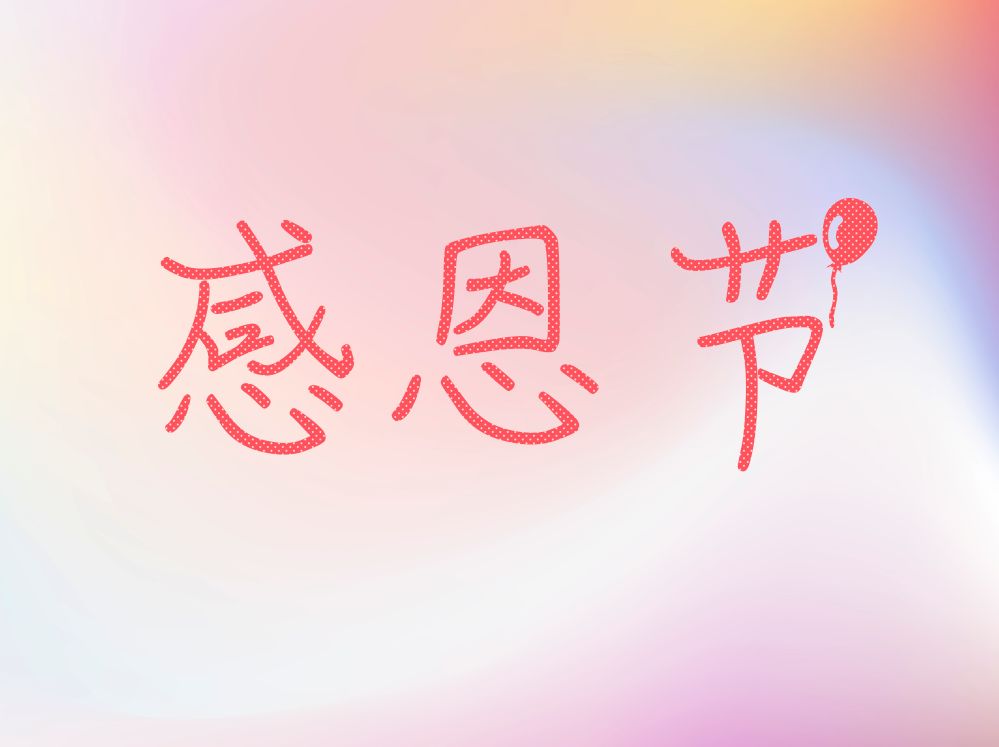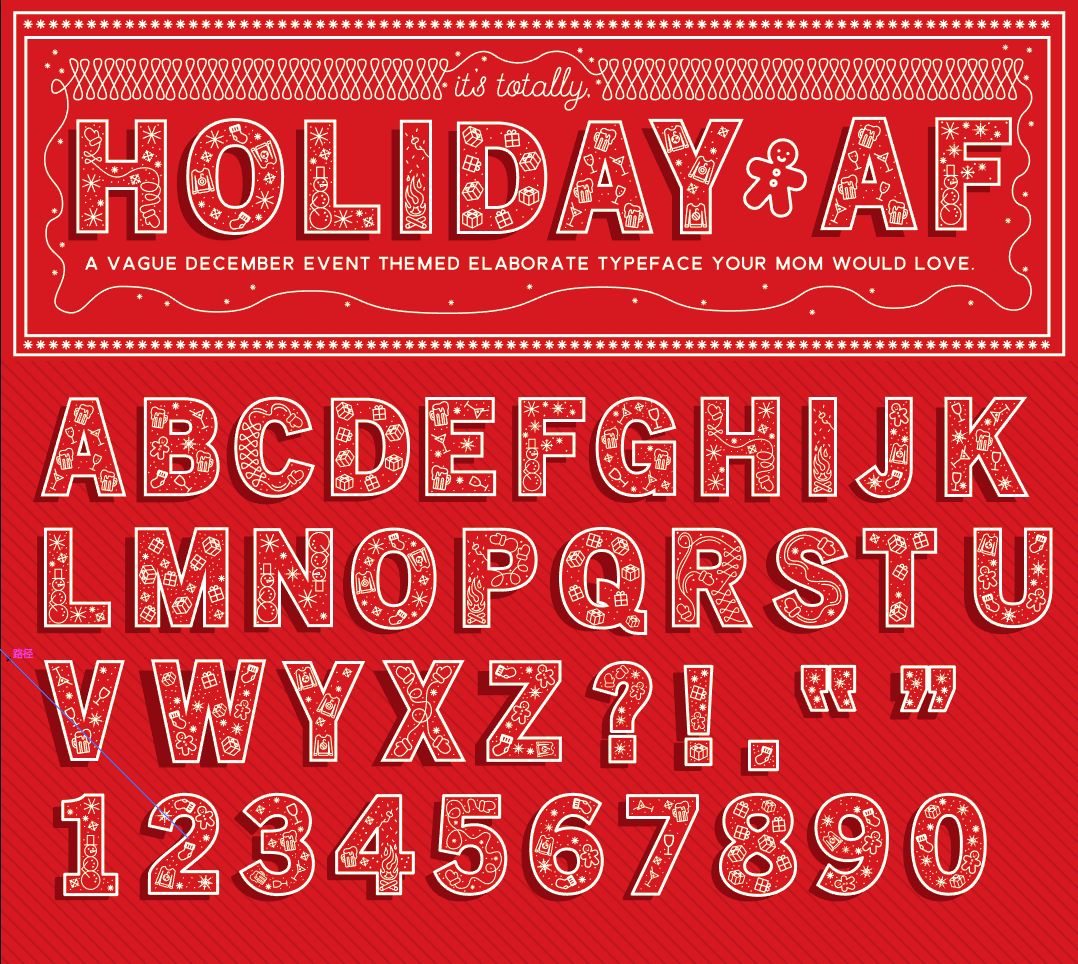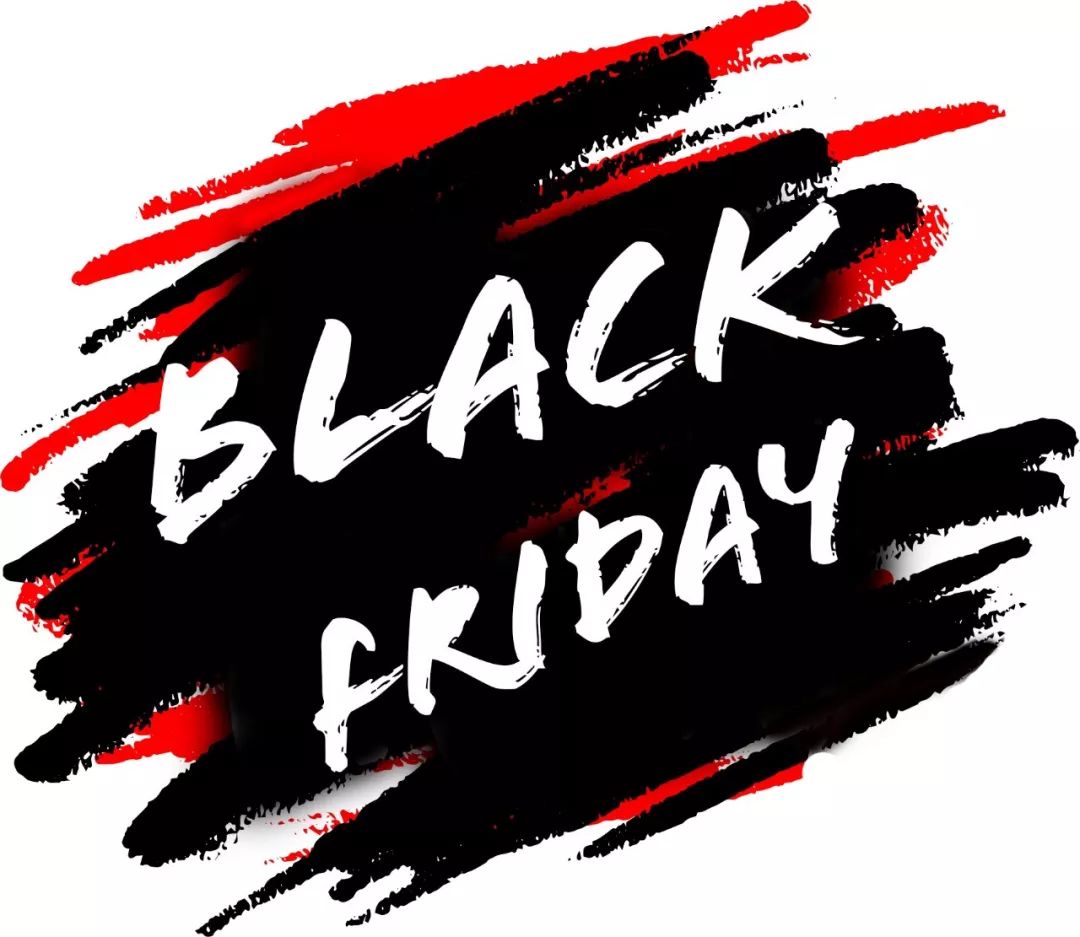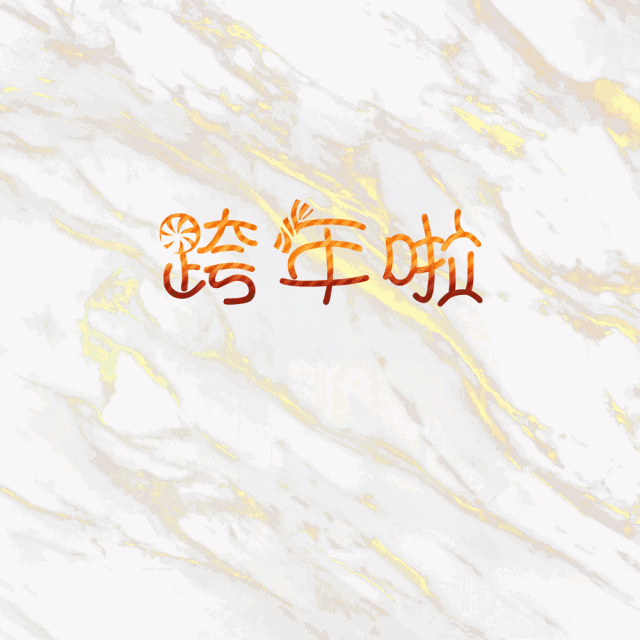
节日海报字体、笔刷、纹理等素材大全
今天柚子想告诉你一个好消息or一个坏消息,你想先听哪个?
好消息是又有一大波节日要来了,你的假期存折可以提前支取了,开不开心~
但不幸的是,在那之前你得把海报啊、页面啊、ppt啊……加班加点做好了,丧不丧,还不如痛快地给我一刀~
我给你估摸算了一下,接下来的大概有感恩节、黑色星期五、双十二、圣诞节、元旦、春节、情人节,都在向你招手,哈哈!
感恩节
感恩节主打温情路线,所以无论颜色上,还是细节上都要烘托一种有爱的气氛。先选择一张背景图,打开字由,搜索ID心之烙印体简,点睛之笔就是那个气球。
这种背景也很适合感恩节,色彩舒缓,又有高贵感,最后会给你高清像素的,不急哈。
如果还觉得不够,可以用这24个ps笔刷,全是西方围绕感恩节的元素,什么南瓜、烤火鸡、橡子啦,还有枫叶、树枝等,每个分辨率约为2500像素,只要载入到画笔,就可以随便刷~刷~刷~了。
感恩节系列的图标我也给你找到了,棒不棒,ui、logo设计的你一定需要它。
既然要感恩,当然就离不开鲜花,这些都psd分层了,想要哪朵都可以。
黑色星期五
黑色星期五和感恩节挨在一起,绝对是有深意的,全家一起欢聚后,第二天再去血拼,超带劲的,所以设计上就是要醒目再醒目!用字由搜索Flood Std,配合红黑背景,超霸气有木有!
背景上我找了一些动物纹理,特别适合御姐抢货,嗯,很有画面感!
圣诞节
每年的圣诞节感觉都差不多,所以我今天给你看点新鲜的,字由客户端有两款圣诞专属字体Christmabet、ChristmasEve。
除此之外,也有这种很有气氛的艺术字,最后会AI格式给你哦~
柚子特别喜欢这种金边装饰元素,所以给你找来了,都是png免抠的。
背景如果找不到合适的,完全可以用笔刷,看起来更自然,又学到一招不是。
还有一些圣诞元素的shape、ps笔刷啊,太多了,你去合集找吧,只不过用的时候,千万别眼花缭乱啊!
偏复古的插画元素,是不是眼前一亮,比传统的更有感觉吧!
跨年、元旦
终于来到跨年了,什么灯光啊、烟花啊、喷溅啊,怎么热闹怎么来呗,反正笔刷已给你备好了。
各种金箔元素也是我的最爱,只要加一点点,就高级死了。
我在字由选了一款ID糖果体简,搭配各种纹理都很有意思。